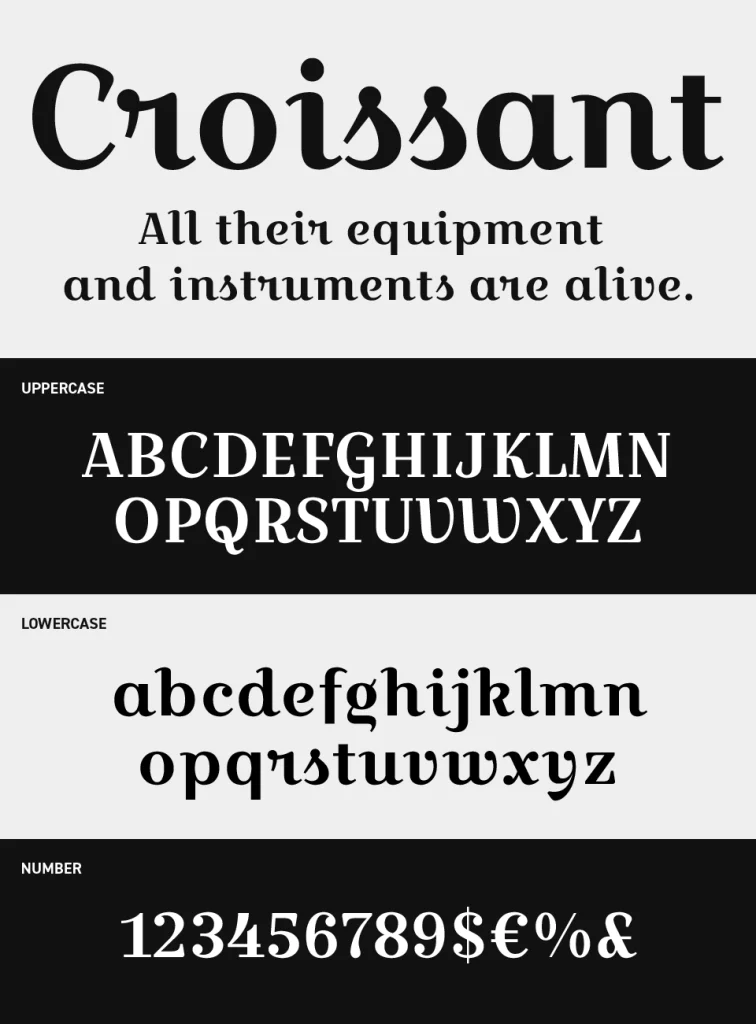
Croissant Font
Croissantフォントは、クラシカルな欧文セリフ体に柔らかな装飾性を加えた、上品でどこかヨーロッパらしい雰囲気を持つエレガントなフォントです。
流れるような曲線と美しいセリフが印象的で、伝統的で洗練された空気感を演出できます。
一部の文字に加えられた独特なカーブやアクセントが、シンプルなセリフ体にはない華やかさを生み出しています。カフェブランド、洋菓子パッケージ、アンティークデザイン、ブライダル関連など、繊細でクラシカルな世界観づくりに向いているフォントです。